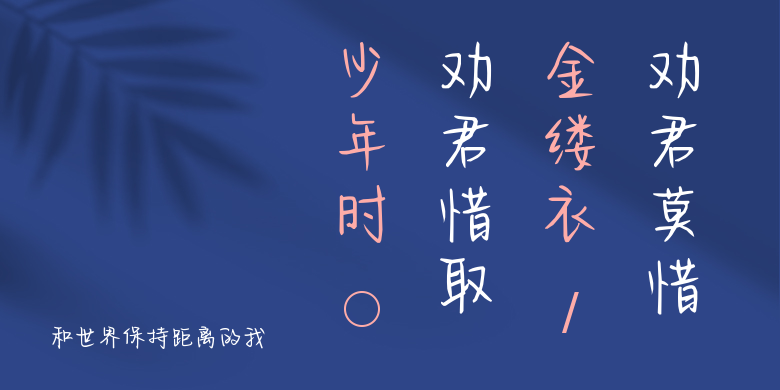
和世界保持距离的我
和世界保持距离的我,这款字体结构工整、笔画清晰,兼顾美观与易读性,适用于标题、正文、海报、包装、LOGO 等多种场景。字形优雅稳定,风格百搭耐看,适配日常排版与创意设计,让文字呈现更舒适、更具质感。和世界保持距离的我一笔一画,皆是细节,以均衡的比例、流畅的线条打造舒适视觉体验,字形端正大气,风格简约现代。无论是商业设计、品牌宣传还是日常排版,都能轻松驾驭,让文字更有格调与力量。和世界保持距离的我字体下载。